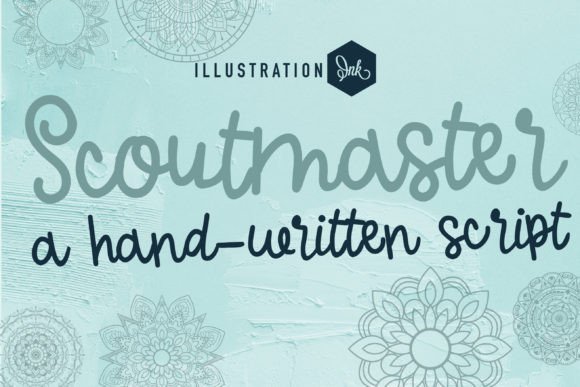
Scoutmaster
Mencari elemen desain yang tepat bisa jadi sulit, namun Scoutmaster menawarkan koleksi luar biasa yang akan langsung meningkatkan kualitas karya Anda.
Dibuat dengan presisi, Scoutmaster menyediakan vektor yang bersih, tipografi yang halus, serta lisensi komersial untuk ketenangan pikiran Anda.